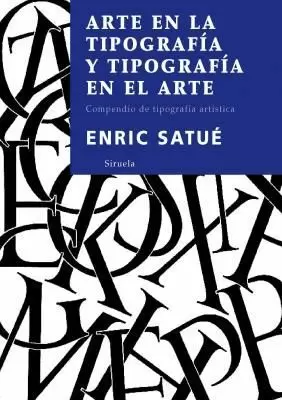
ARTE EN LA TIPOGRAFÍA Y TIPOGRAFÍA EN EL ARTE
COMPENDIO DE TIPOGRAFÍA ARTÍSTICA
SATUÉ, ENRIC
Según el concepto platónico de belleza, ésta se manifiesta en los objetos que son simplemente útiles. Siendo así, la radical utilidad de la tipografía exalta la suya en una epifanía tan espléndida en su variedad como recatada en su ostentación. En efecto, pese a tenerla siempre a la vista, la tipografía resulta casi invisible. Arte en la tipografía y tipografía en el arte propone contemplar esa belleza útil desde un ángulo apasionado, ofreciendo algunas de las más geniales creaciones, modelos o prototipos. Si el tipo de imprenta resume tantas propiedades plásticas es porque, como apreció el arquitecto Peter Behrens, «es uno de los más elocuentes medios de expresión de cada época o estilo». Además, numerosos artistas plásticos del siglo XX han reparado también en la belleza de la tipografía, añadiendo letras de imprenta a sus composiciones y destacando con sus obras de arte el arte que permanece oculto en la tipografía ante la distraída mirada del mundo.